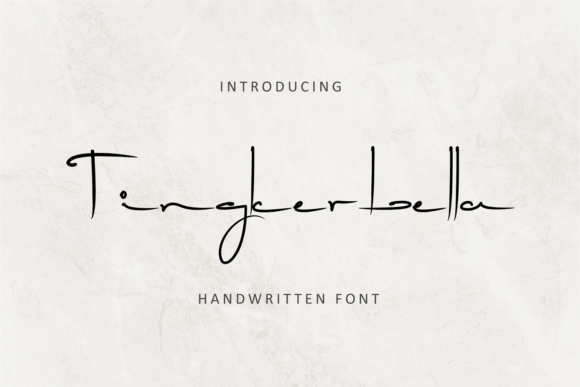
Tingkerbella Script Font – Download Grátis
A Tingkerbella Handwritten Font é uma opção incrível para quem busca dar um toque autêntico a suas criações digitais. Introduzida pelo designer M.0Type, esta fonte script é perfeita para os designers que valorizam um visual natural e cuidadosamente elaborado. Tingkerbella possui um estilo totalmente handwritten, o que proporciona uma sensação de personalização e arte manual direto ao seu design. Suas linhas fluidas e suas formas delicadas criam um ar de sofisticação casual, tornando-a perfeita para aplicações como água-marinha em fotografias, assinaturas ou logotipos digitais, capas de álbum e cartões de negócio. Também é uma escolha ótima para texturas como citações ou qualquer outro projeto gráfico que busque um toque mais pessoal.